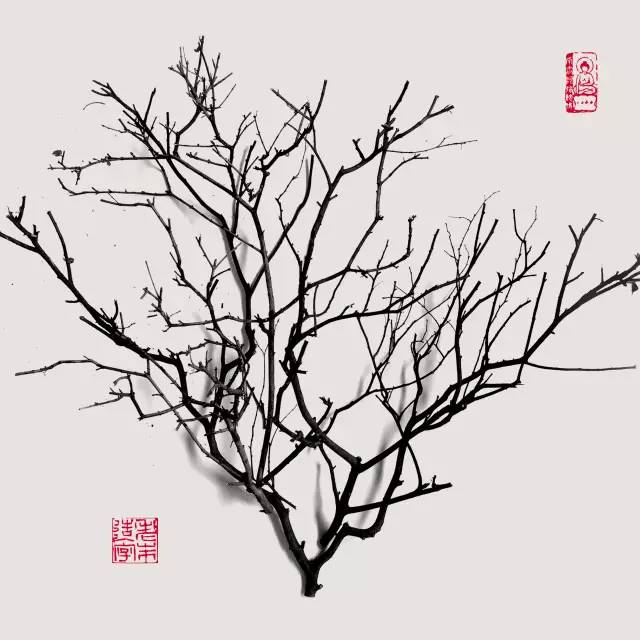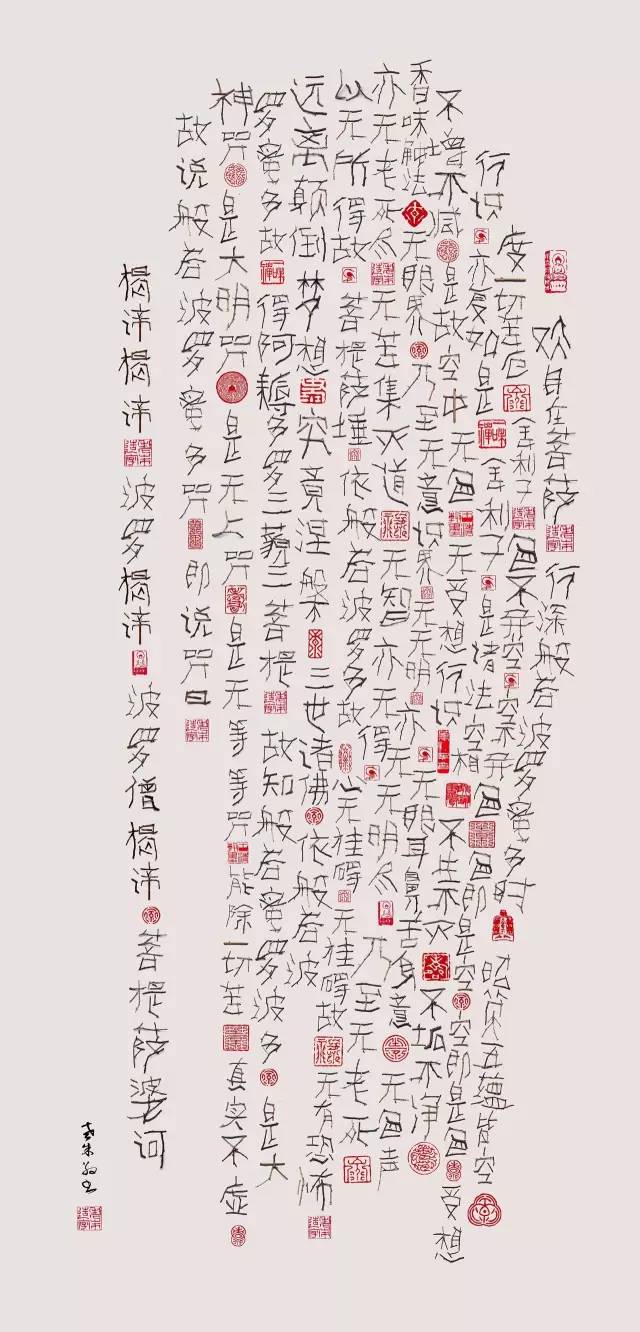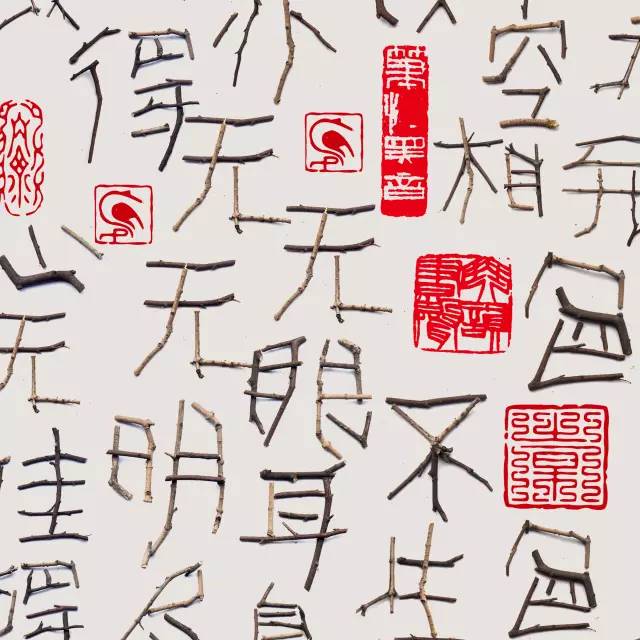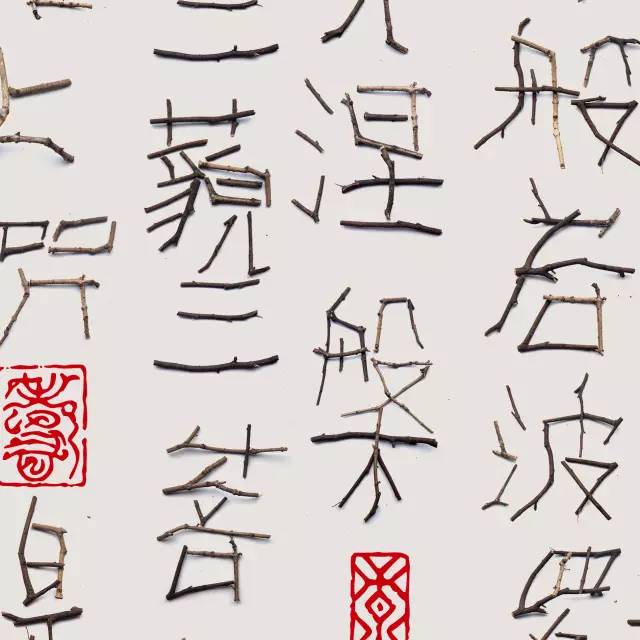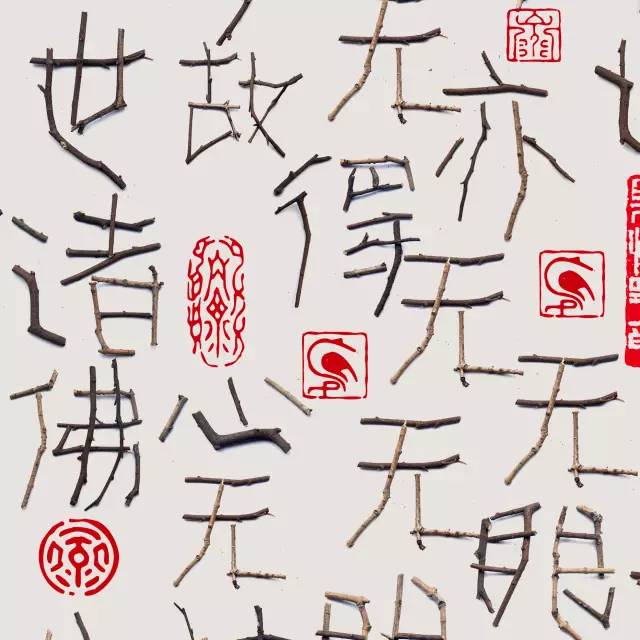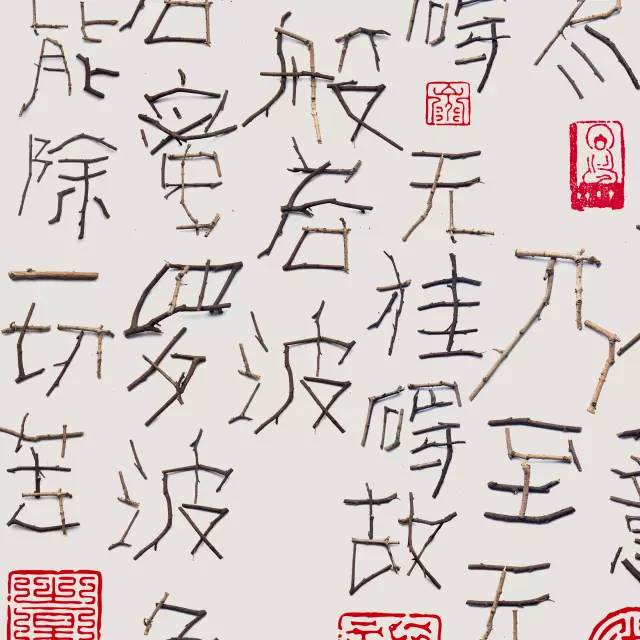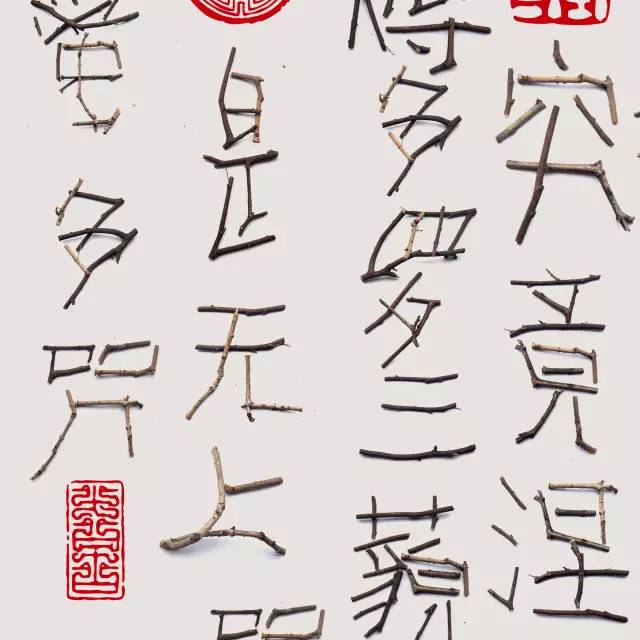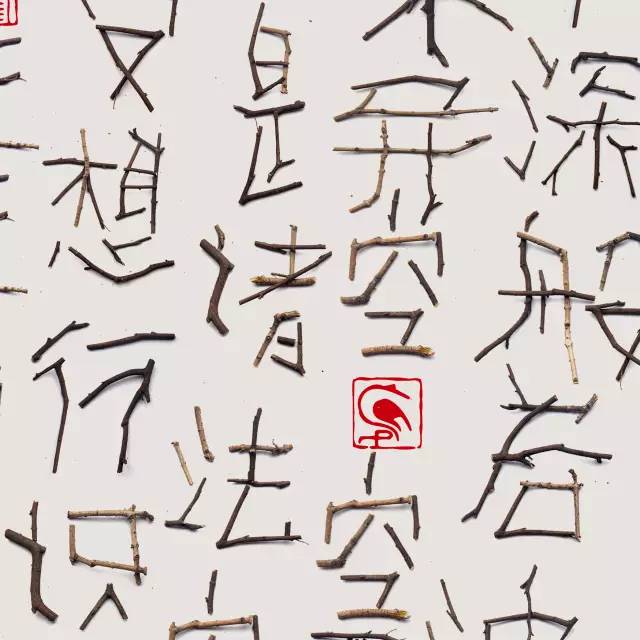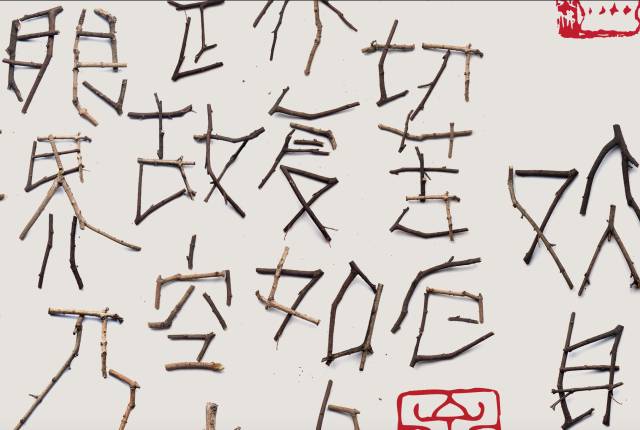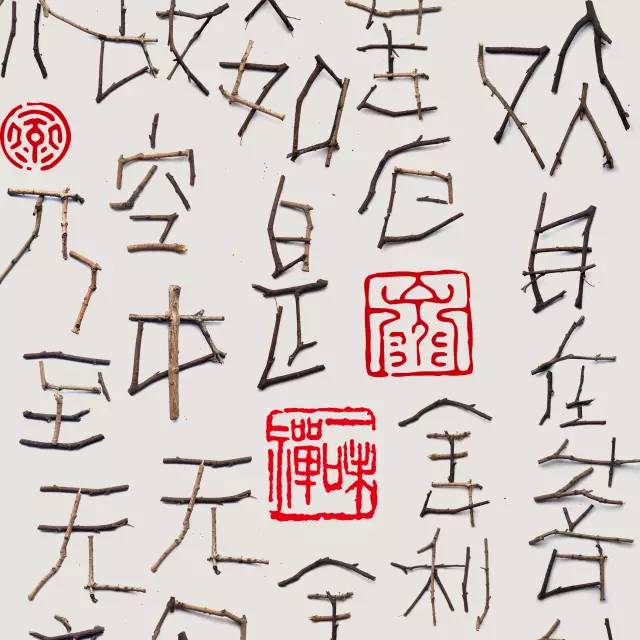
老朱造字-心经-树枝造字探索,字体设计案例
在心经创作时,把干枯的树枝拣回,通过以树枝自然的形态重新组合,把心经一个字一个字组合,拍照。在这当下的过程是充满的,不是刻意感觉,是自然体会,是一次对心经的感悟,对自我心灵的一次洗涤,当我提起正念创作的时候,就是在练习回归当下,以便活在此时此地。当身心完全安住当下时,一个个字便会清晰地显现在面前,这是一种美妙的存在。这正是:树枝在手中,正念直提起,吾心与吾身,安住此时地。